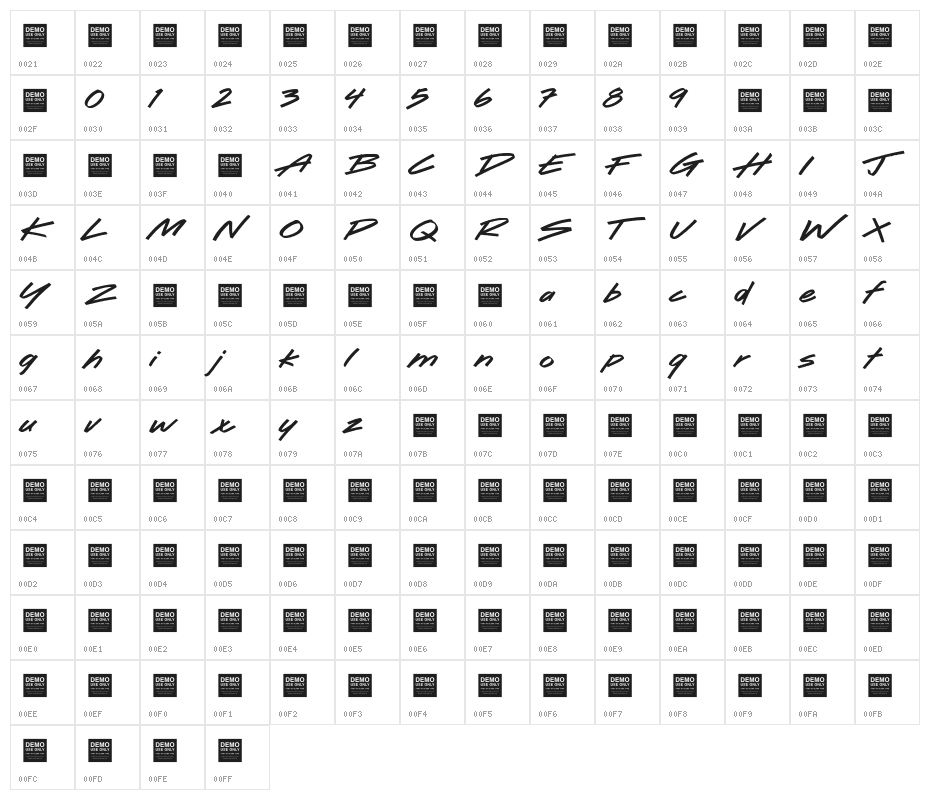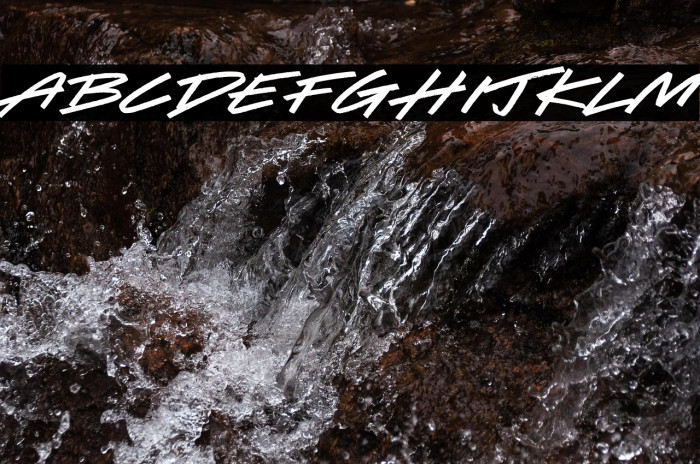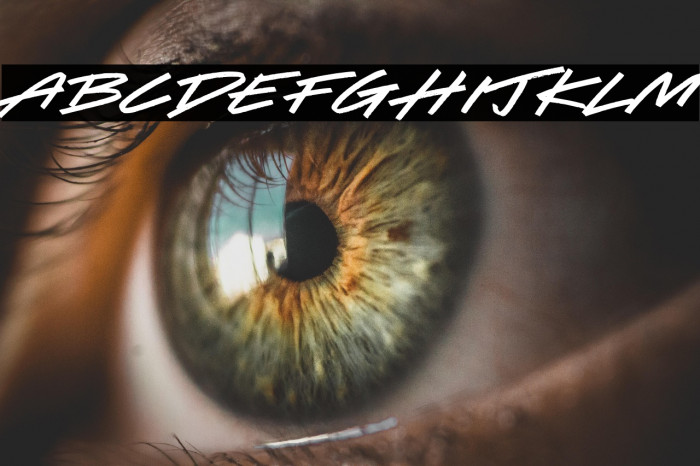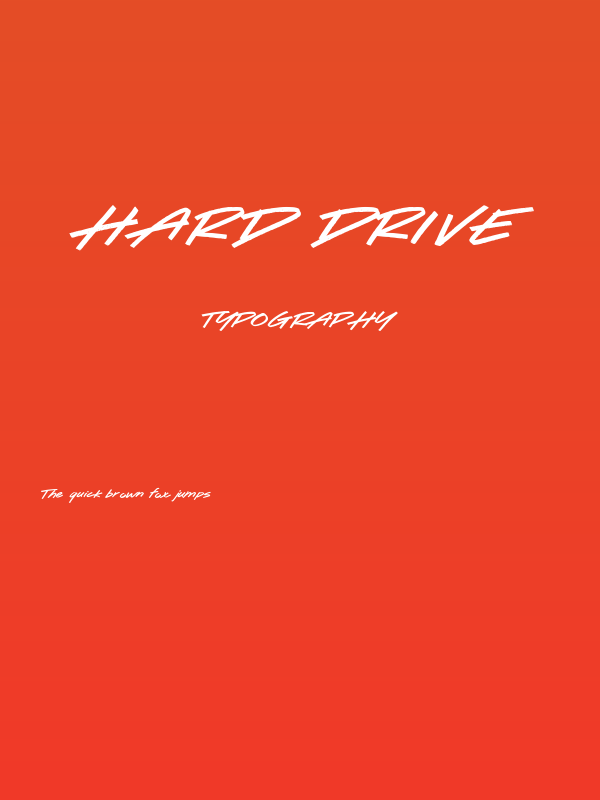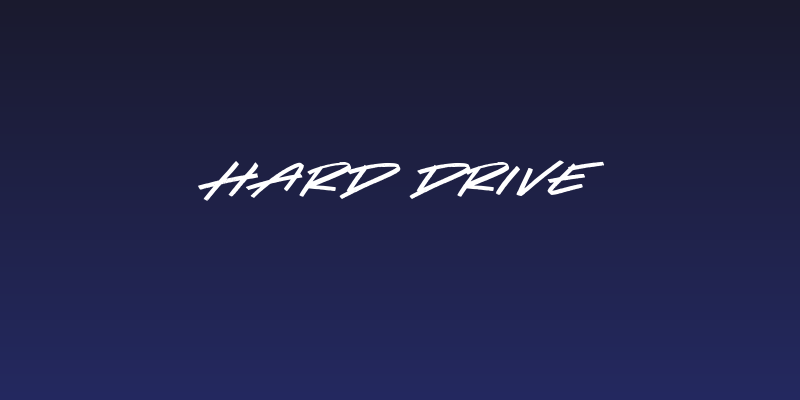
Hard Drive Font
| Caso d'uso | Logos, Headlines, Invitations |
| Progetti proposti | Ideal for branding, logos, invitations, and any design that benefits from a personal, handwritten touch. |